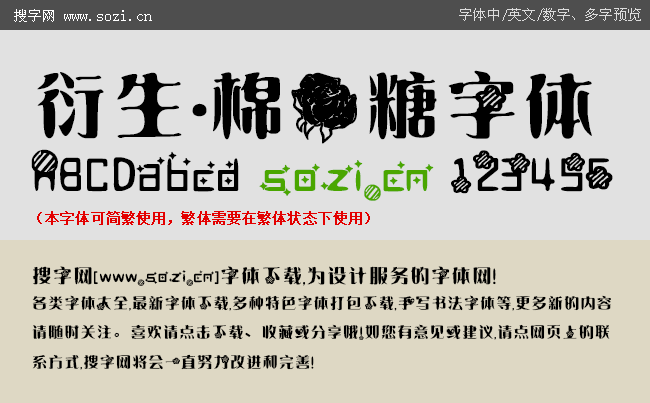
衍生·棉花糖字體
搜字網(wǎng)給大家提供一款衍生·棉花糖字體手機(jī)中文字體下載。這款手機(jī)字體是以粗宋體為原形進(jìn)行藝術(shù)變形,筆畫(huà)間又插入了漂亮的花朵圖案。該字體大方得體,充滿趣味性,特別適合喜歡手機(jī)字體個(gè)性一些的朋友在手機(jī)上安裝使用。